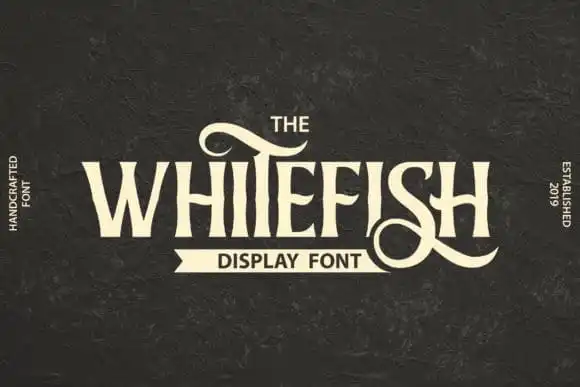
Whitefish Display Font – Download Grátis
A Whitefish Display Font é uma tipografia de destaque composta por letras maiúsculas projetadas para ser simples, inspirada em posts sociais e livros de letras. Foi criada pelo designer AZetype com um visual elegante e vintage, ricos em swashes que chamam atenção. Esta fonte exala estilo e sofisticação, sendo perfeita para destacar qualquer projeto gráfico. Seja você um artista digital ou profissional de design, essa fonte irá adicionar uma camada única e atraente ao seu trabalho. Não deixe suas criações se perderem na multidão — use a Whitefish Display Font para garantir que sua obra seja vista e lembrada.